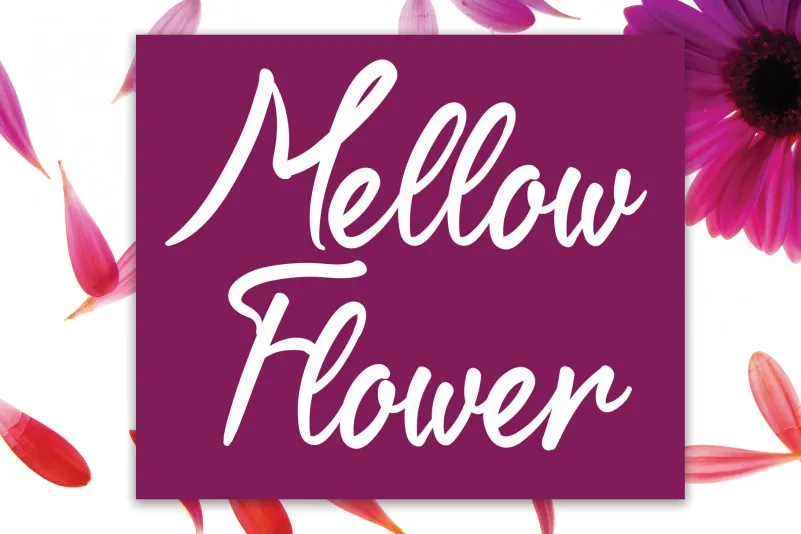
Mellow Flower Script Font – Download Grátis
A Mellow Flower Script Font é uma elegante fonte manuscrita que transmite a sensação de calma e alegria. Seu design fluído e relaxado é perfeito para aqueles designers buscando uma fonte suave e encantadora. É como se você estivesse assistindo um artista florido criar trabalhos delicados com o dedo, deixando rastros de amor nas páginas. A Mellow Flower Script Font é ideal para qualquer projeto que deseja transmitir emoções leves e alegres, seja em logotipos de marca, cartões personalizados ou designs digitais. Ela traz uma sensação de paz e simplicidade, tornando-a perfeita para aqueles designers buscando um equilíbrio elegante e natural.